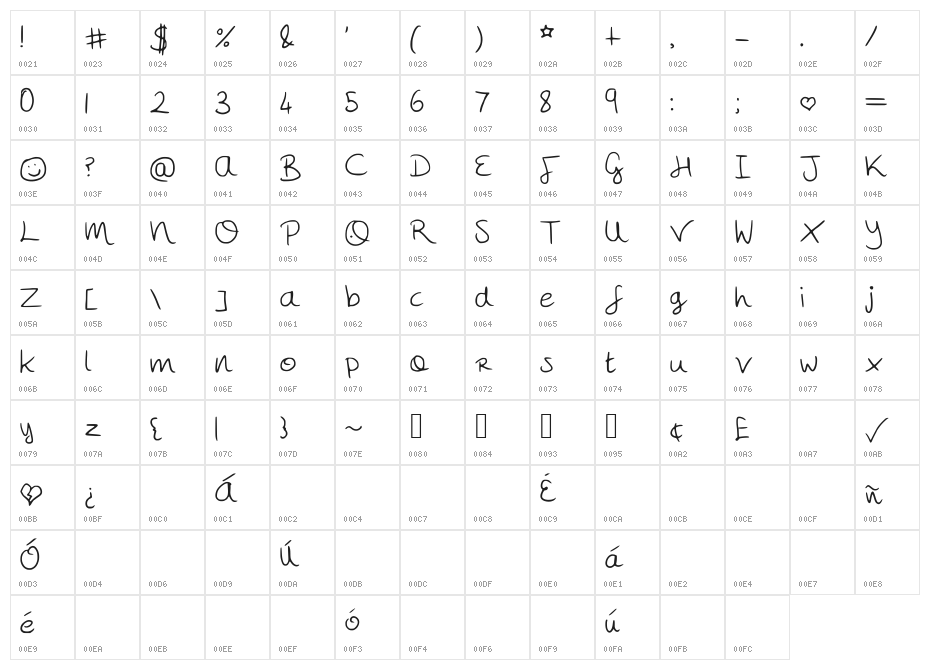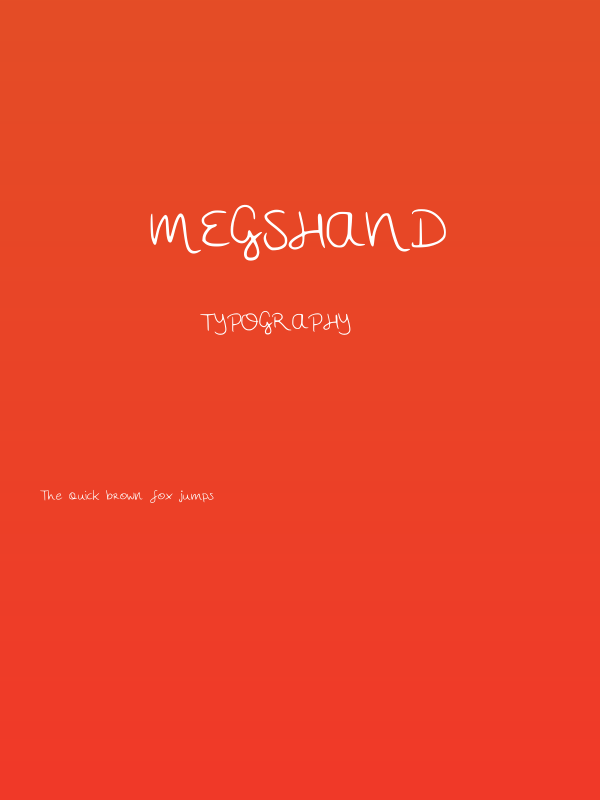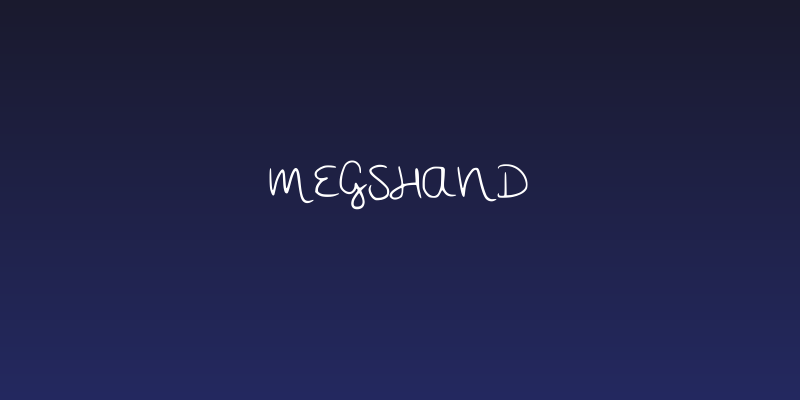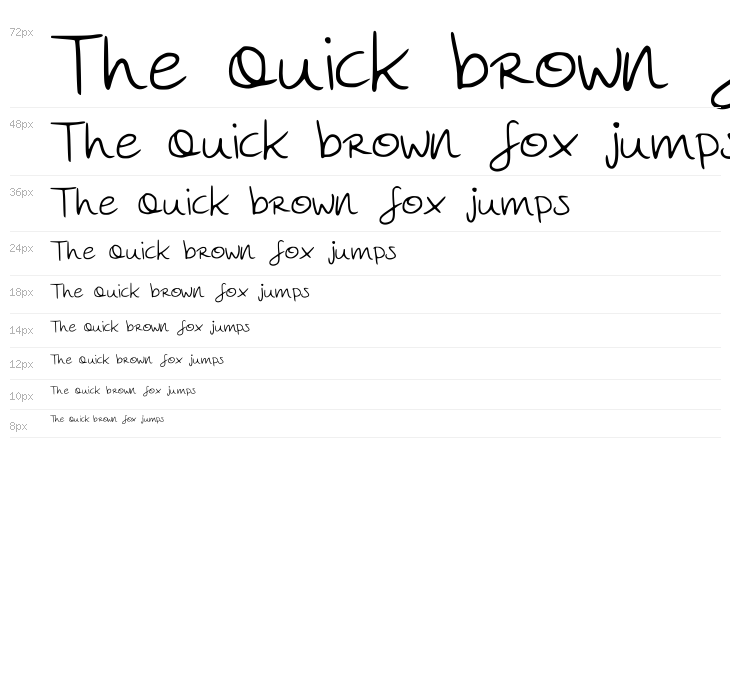
MegsHand Font
| Gesamtstil | Casual, Playful |
| Anwendungsfall | Logos, Headlines, Informal Text |
| Vorgeschlagene Projekte | Ideal for greeting cards, invitations, personal branding, and casual social media graphics. |